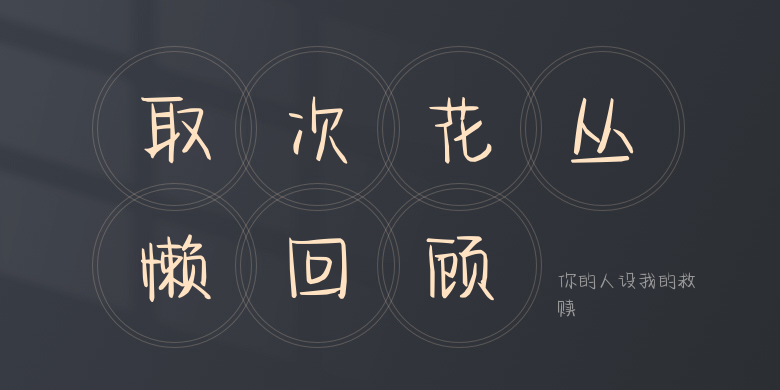
你的人设我的救赎
你的人设我的救赎,这款字体结构工整、笔画清晰,兼顾美观与易读性,适用于标题、正文、海报、包装、LOGO 等多种场景。字形优雅稳定,风格百搭耐看,适配日常排版与创意设计,让文字呈现更舒适、更具质感。你的人设我的救赎一笔一画,皆是细节,以均衡的比例、流畅的线条打造舒适视觉体验,字形端正大气,风格简约现代。无论是商业设计、品牌宣传还是日常排版,都能轻松驾驭,让文字更有格调与力量。你的人设我的救赎字体下载。